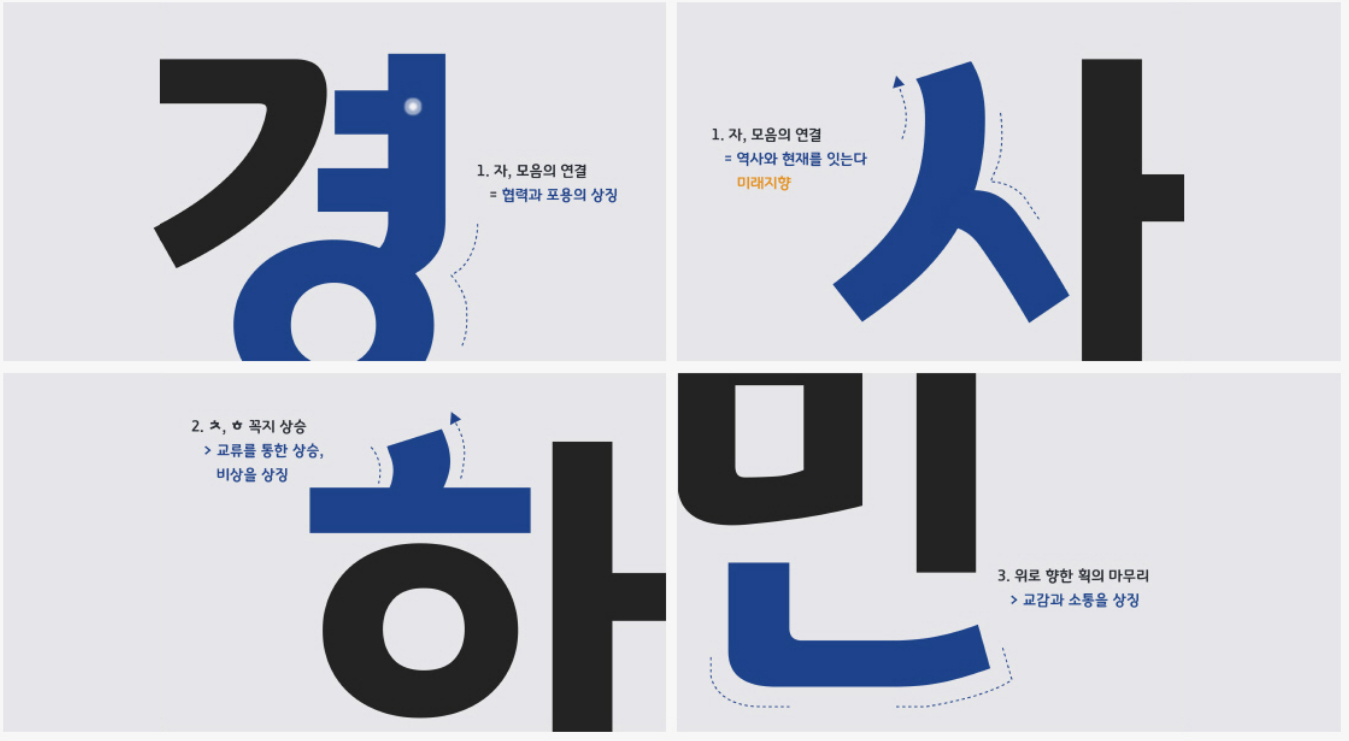
경기도 서체, 천년 역사의 숨결을 담은 디자인
경기도는 대한민국의 수도권을 중심으로 발전한 광역자치단체입니다. 2021년 12월 13일, 경기도는 천년 역사를 기념하는 의미로 자체 개발한 서체 '경기천년체'를 공식 출시했습니다. 이 글에서는 경기천년체의 디자인 특징, 개발 배경, 활용 방안 등을 자세히 살펴보면서, 경기도의 정체성을 보여주는 독창적인 서체로서의 매력을 소개하고자 합니다.
경기천년체의 디자인 특징
경기천년체는 '이음'이라는 콘셉트를 기반으로 디자인되었습니다. 이는 한반도의 동서남북을 연결하는 경기도의 지정학적 특성과, 타 지역 대비 유연하고 융통성 있는 도민의 인성을 반영한 것입니다. 또한, 천년 역사를 이어온 경기도의 깊이와 아름다움을 표현하기 위해 전통적인 한국 서체의 느낌을 살리면서도 현대적인 감각을 더했습니다.
자음과 모음의 유연한 연결
경기천년체의 가장 큰 특징은 자음과 모음의 유연한 연결입니다. 특히, 자음 끝자락이 위로 올라가는 듯한 디자인은 마치 '이음'이라는 콘셉트를 시각적으로 표현한 것 같습니다. 이러한 디자인은 글자의 흐름을 부드럽게 만들고, 시선 이동을 용이하게 하여 독자의 편의를 높여줍니다.
꼭지 모양과 받침의 마무리 상승
경기천년체는 꼭지와 받침의 끝부분이 위로 올라가는 디자인을 사용했습니다. 이는 글자의 균형감을 유지하고, 시각적으로 안정감을 주는 효과가 있습니다. 또한, 마치 앞으로 나아가는 듯한 느낌을 주어 경기도의 역동적인 이미지를 표현합니다.
풍부한 글자 변형
경기천년체는 다양한 글자 변형을 제공합니다. 이는 일반적인 바탕글자, 제목글자, 굵은글자, 기울임글자뿐만 아니라, 액자글자, 그림자글자, 윤곽선글자 등을 포함합니다. 이처럼 풍부한 글자 변형은 디자이너들에게 다양한 표현 도구를 제공하며, 콘텐츠 제작의 효율성을 높입니다.
경기천년체 개발 배경
경기천년체는 경기도의 천년 역사를 기념하고, 도민 정체성을 보여주는 독창적인 서체를 개발하려는 목표로 제작되었습니다. 기존에 사용하던 나눔고딕이나 본고딕은 다른 지역과의 차별성이 부족하고, 경기도의 특징을 잘 나타내지 못한다는 지적이 있었습니다. 이러한 문제점을 해결하기 위해 경기도는 자체 서체 개발을 추진하게 되었고, 2021년 12월 13일 경기천년체를 공식 출시했습니다.
경기천년체 개발에는 국내 유수의 서체 디자이너들이 참여했습니다. 디자이너들은 경기도의 역사, 문화, 자연 등을 연구하며 경기도만의 독특한 이미지를 담아낼 수 있는 서체를 디자인했습니다. 또한, 도민들의 의견을 수렴하여 서체를 개선하는 과정도 거쳤습니다.
경기천년체는 경기도의 공식 서체로서, 도청, 공공기관, 학교 등 다양한 기관에서 활용되고 있습니다. 또한, 민간 기업에서도 경기천년체를 사용합니다.
경기천년체는 민간 기업에서도 사용되고 있습니다. 특히, 경기도 지역 기업들은 자사의 브랜드 이미지를 강화하고, 지역 사회와의 소통을 높이기 위해 경기천년체를 적극 활용하고 있습니다. 또한, 디자이너들은 경기천년체를 사용하여 다양한 디자인 작품을 제작하고 있습니다.
경기천년체는 출시된 지 얼마 되지 않은 만큼 아직 널리 사용되고 있지는 않지만, 앞으로 경기도의 대표 서체로 자리 잡을 것으로 기대됩니다. 경기천년체는 경기도의 정체성을 보여주는 중요한 문화자산이며, 지역 이미지를 일관되게 구축하고, 도민들의 자긍심을 높이는 데 기여할 것으로 기대됩니다.
기대 효과
경기천년체는 다음과 같은 기대 효과를 가져올 것으로 기대됩니다.
- 경기도 이미지 제고: 경기천년체는 경기도의 독창적이고 역동적인 이미지를 보여주는 서체입니다. 경기천년체를 활발하게 사용함으로써 경기도의 이미지를 제고하고, 브랜드 가치를 높일 수 있습니다.
- 도민 정체성 강화: 경기천년체는 경기도의 역사와 문화를 담아낸 서체입니다. 경기천년체를 사용함으로써 도민들의 공동체 의식을 함양하고, 도민 정체성을 강화할 수 있습니다.
- 지역 경제 활성화: 경기천년체는 지역 기업의 디자인 자산 활용을 촉진하고, 지역 문화산업 발전에 기여할 것으로 기대됩니다.
경기천년체는 경기도의 천년 역사를 기념하고, 도민 정체성을 보여주는 독창적인 서체입니다. 아름다운 디자인과 다양한 활용 방안을 통해 경기도의 이미지를 제고하고, 지역 경제를 활성화하는 데 기여할 것으로 기대됩니다. 경기천년체를 적극 활용하여 경기도를 더욱 발전시켜 나가기를 바랍니다.